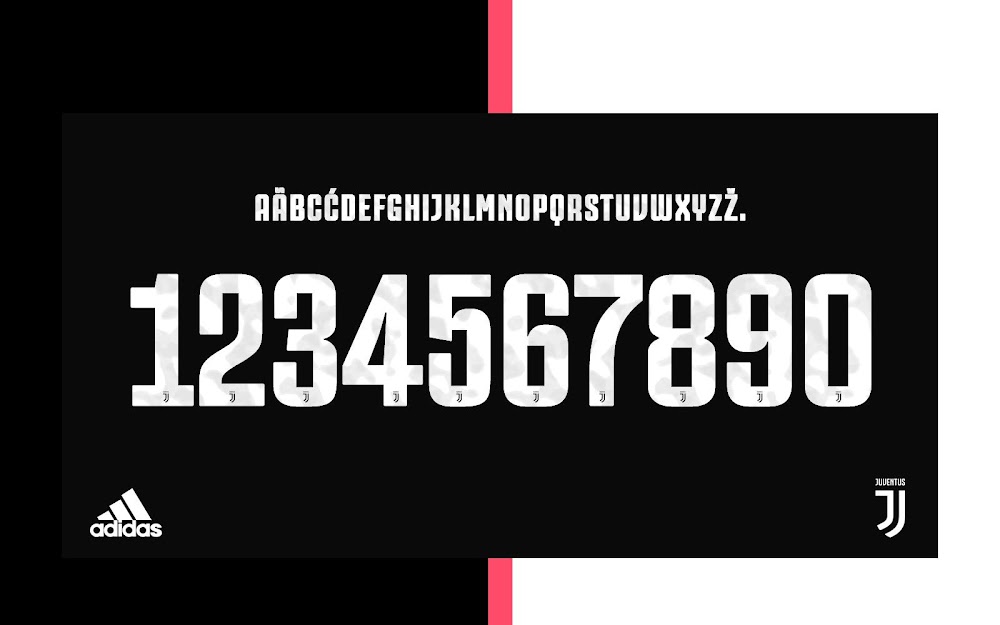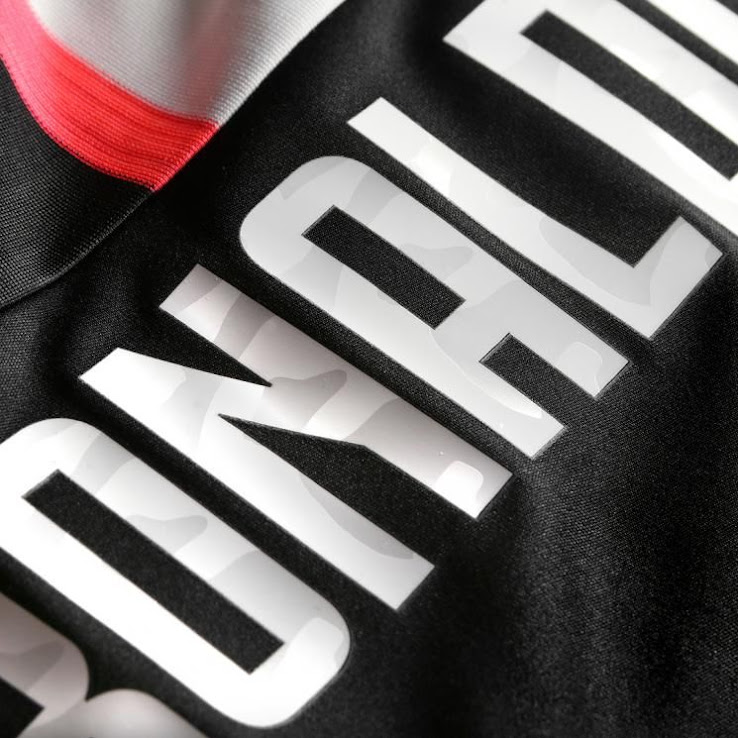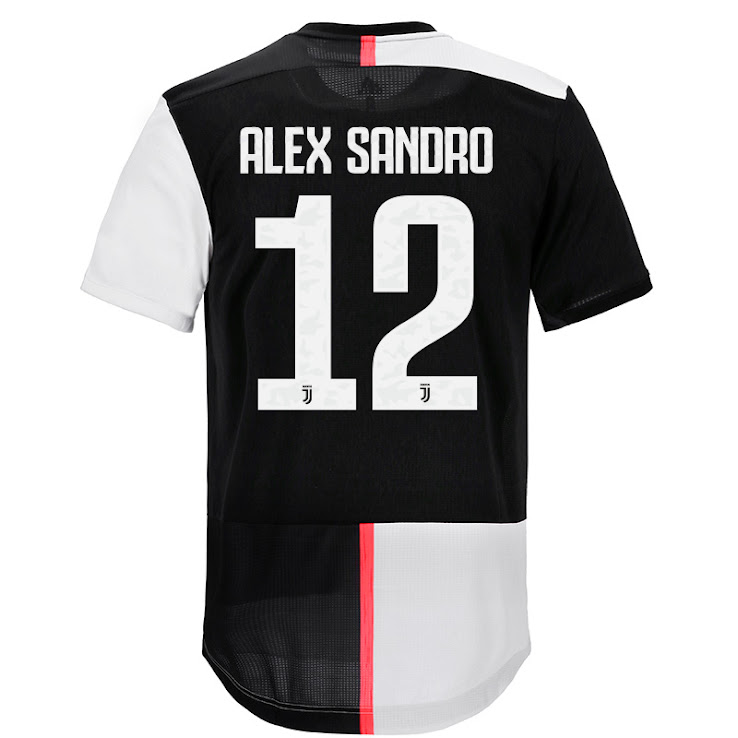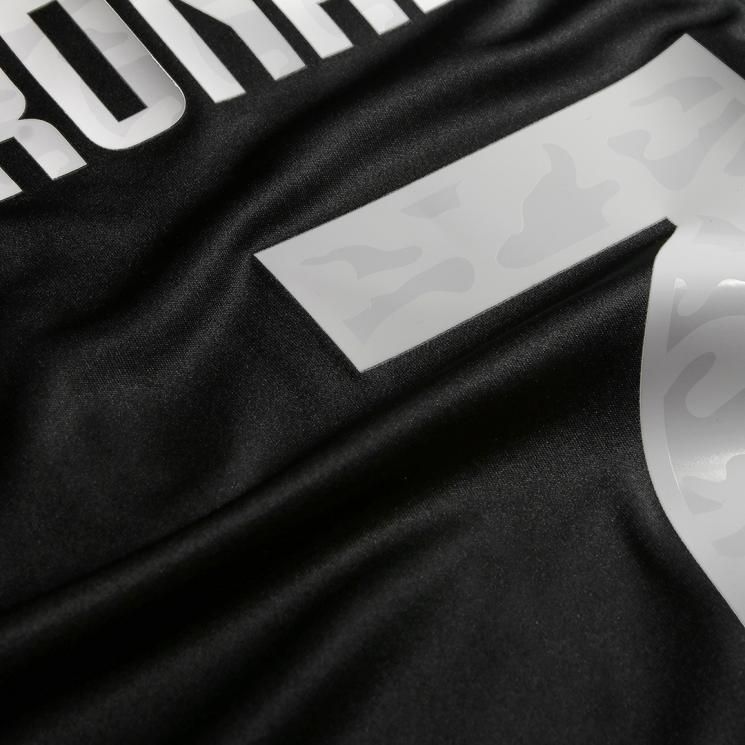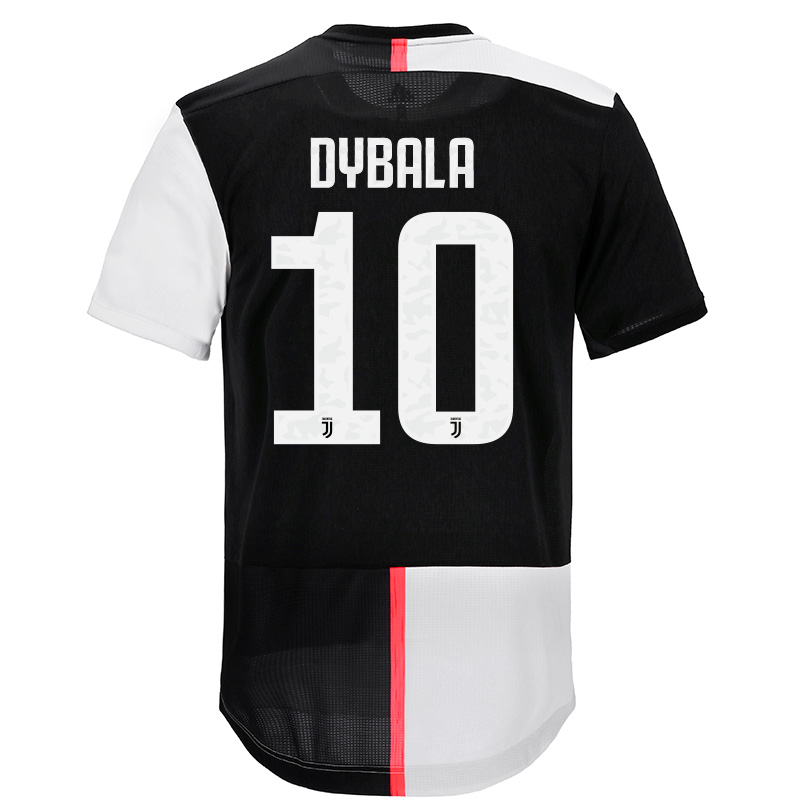
Camo Adidas Juventus 19-20 Trikot-Schriftart Veröffentlicht - Aufgetauchtes Auswärtstrikot Bestätigt
Update: Wir haben weitere Nahaufnahmen und ein Bild aller Nummern und Buchstaben der Adidas Juventus 2019-2020 Trikot-Schriftart hinzugefügt.
Die Adidas Juventus 2019-2020 Trikot-Schriftart weist ein besonderes Muster auf, das ebenfalls das zweite Juventus 2019-2020 Trikot von Adidas bestätigt. Vielen Dank an die Juve-Trikotexperten @La_Bianconera für den Hinweis.
Adidas Juventus 19-20 Trikot-Schriftart
Die Nummern des Adidas Juventus 19-20 Trikots setzen auf ein subtiles Camouflage-Muster - es ist das gleiche Grafikmuster wie auf dem Adidas Juventus 2019-2020 Auswärtstrikot, das noch nicht veröffentlicht wurde.
Abgesehen vom Camouflage-Muster und anderen kleinen optischen Veränderungen ist der Stil der Adidas Juventus 2019-2020 Namen und Nummern identisch mit jenen der Saison 2018/2019.